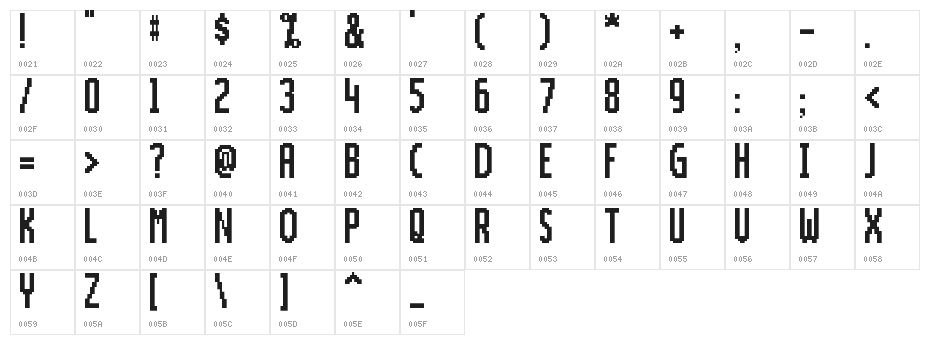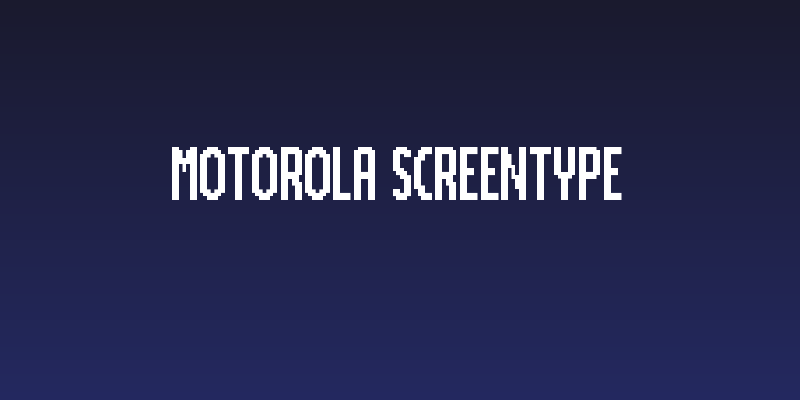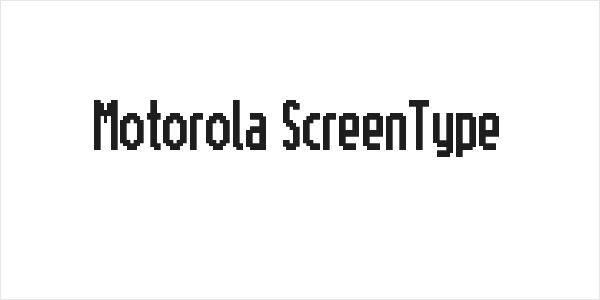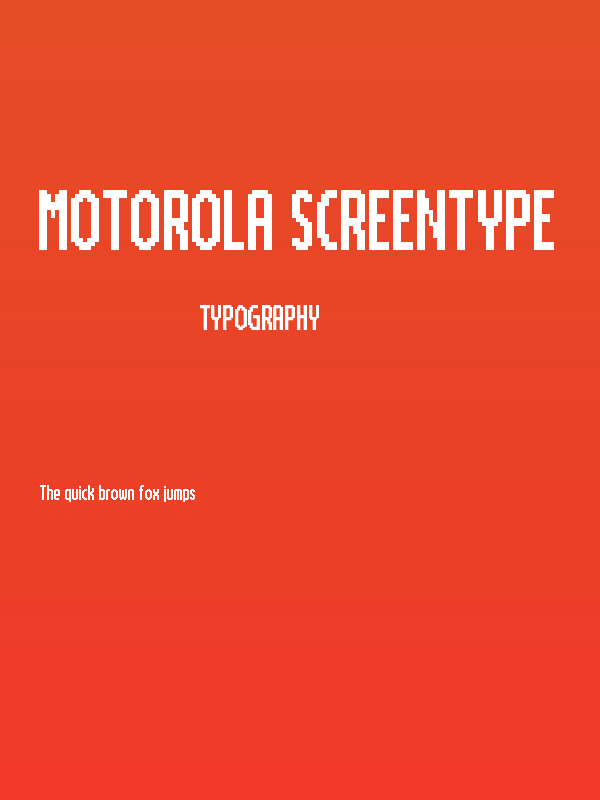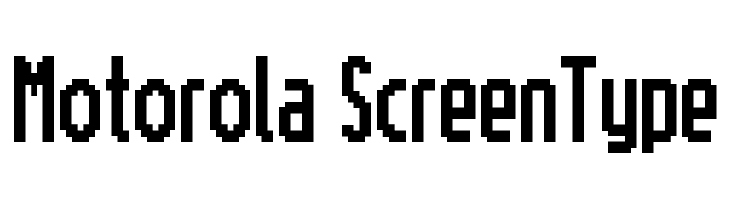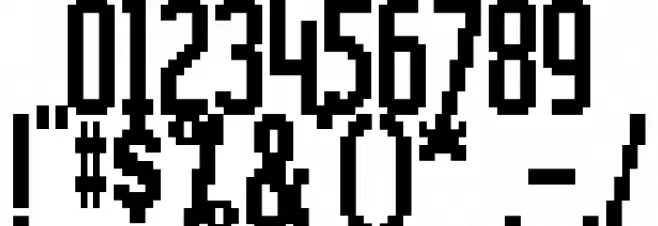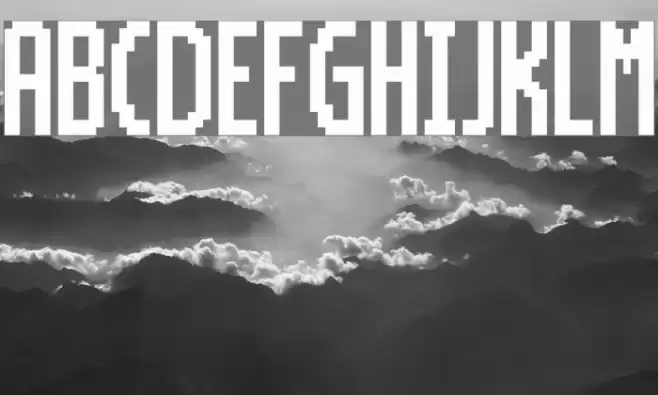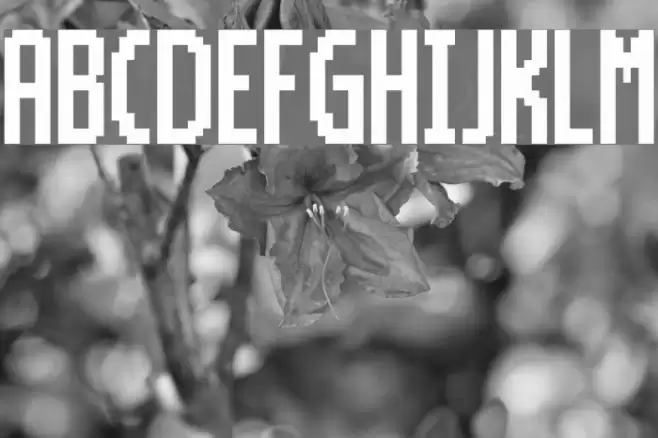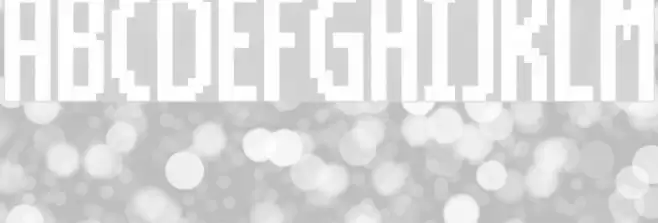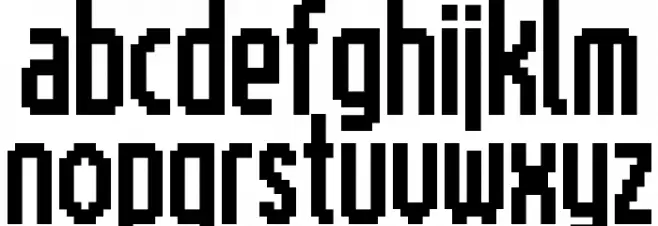
Motorola ScreenType Font
| Gesamtstil | Retro, Digital |
| Anwendungsfall | Logos, Headlines, Posters |
| Vorgeschlagene Projekte | Ideal for retro video game designs, digital-themed posters, tech-related branding, and nostalgic digital art. |